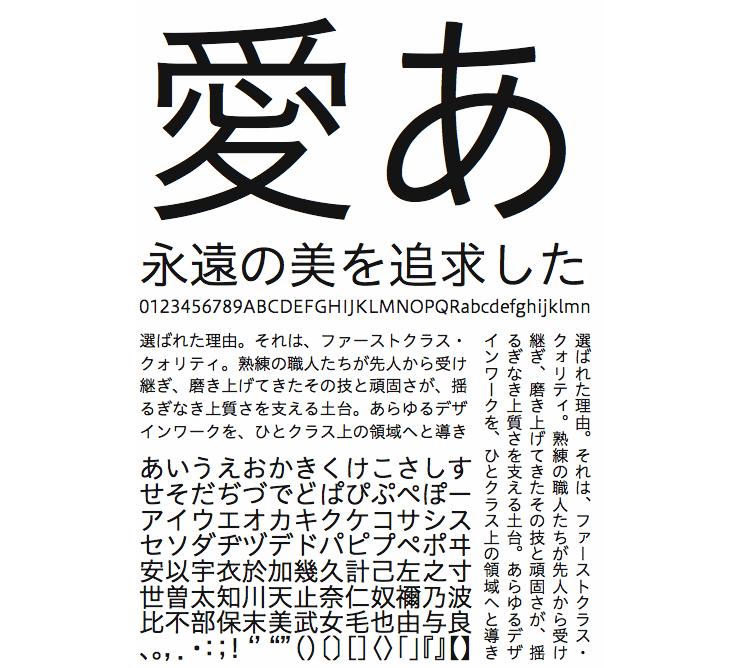
【ヒラギノUD角ゴ】「ヒラギノ角ゴ」の基本デザインを受け継ぐユニバーサルデザインのフォントです。やや小さめの字面で仮名には柔らかな骨格を採用。濁点・半濁点の強調、数字・欧文のオリジナルデザイン採用により判読性を向上。美しいデザイン性とともに長い文章も心地よく読める可読性を提供します。
ヒラギノUD角ゴ StdN W3